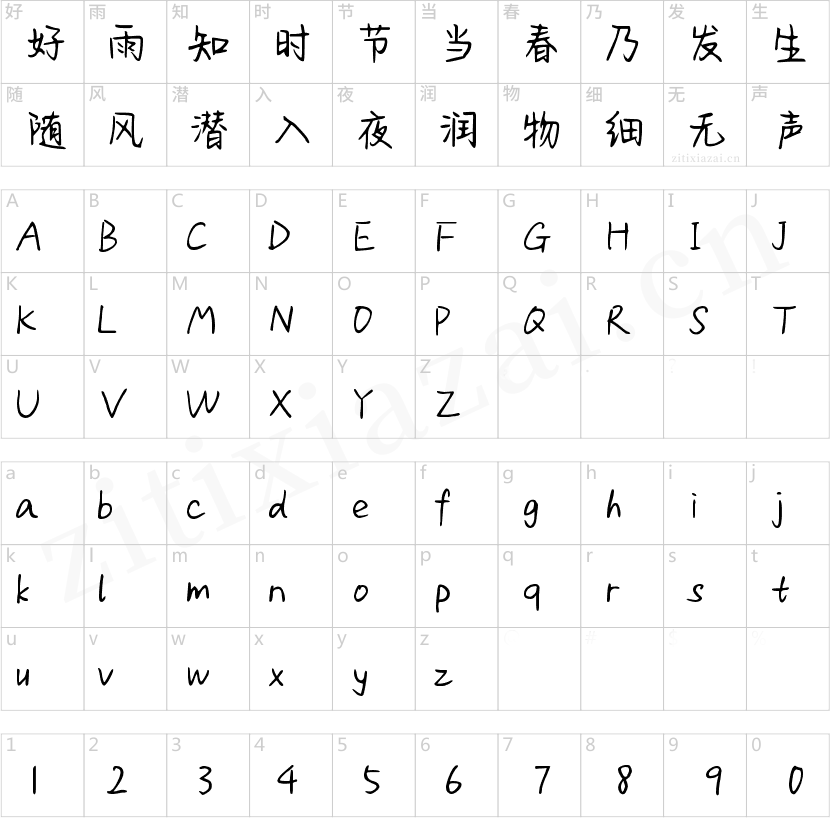
Aa少女の夏日微醺
Aa少女の夏日微醺字体
Aa少女の夏日微醺是一款非常具有艺术性的字体,它的设计灵感来源于对古典艺术的研究,同时又融入了现代字体设计的元素。字形优美,笔画粗细变化自然,给人以大气、典雅的感觉。Aa少女の夏日微醺是一款既传统又现代的字体,它的设计充满艺术感,美观大方,实用性也非常强。无论是对于设计师还是对于普通读者来说,都是一种非常不错的字体选择。Aa少女の夏日微醺适合用于具有艺术感的场合,比如海报、宣传单张、书籍封面等。由于其字形流畅且具有动态感,也适合用于大量的文本排版,如报纸、杂志等。